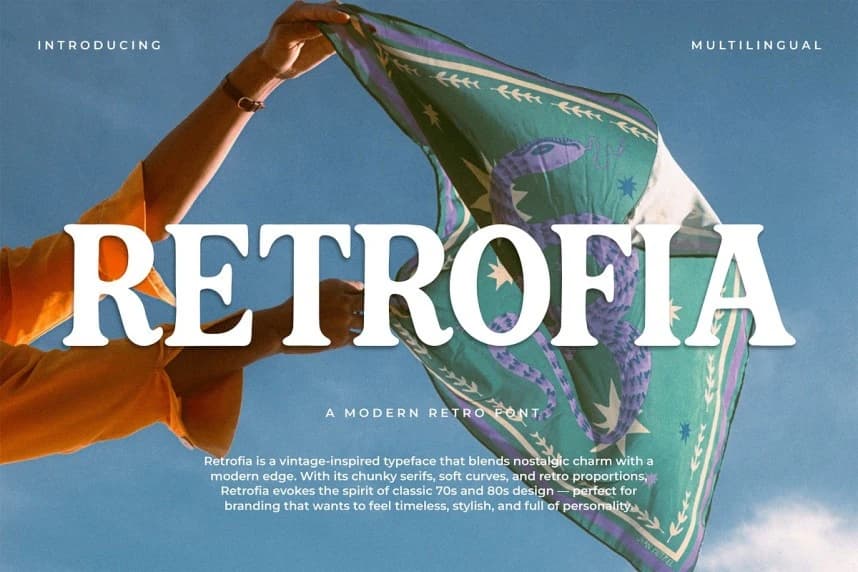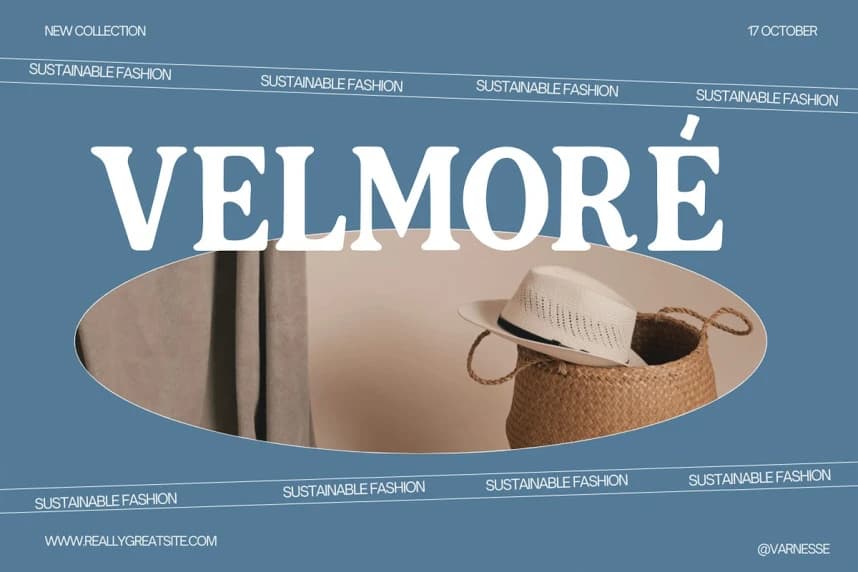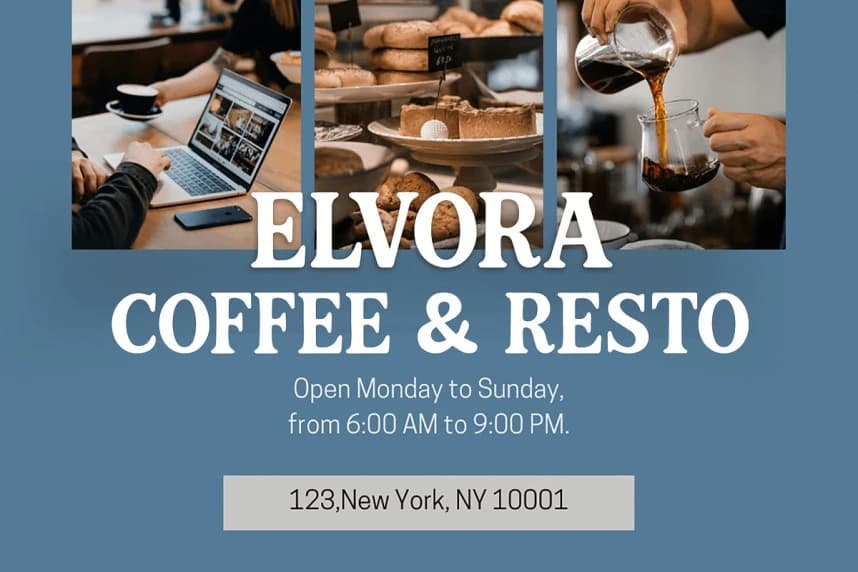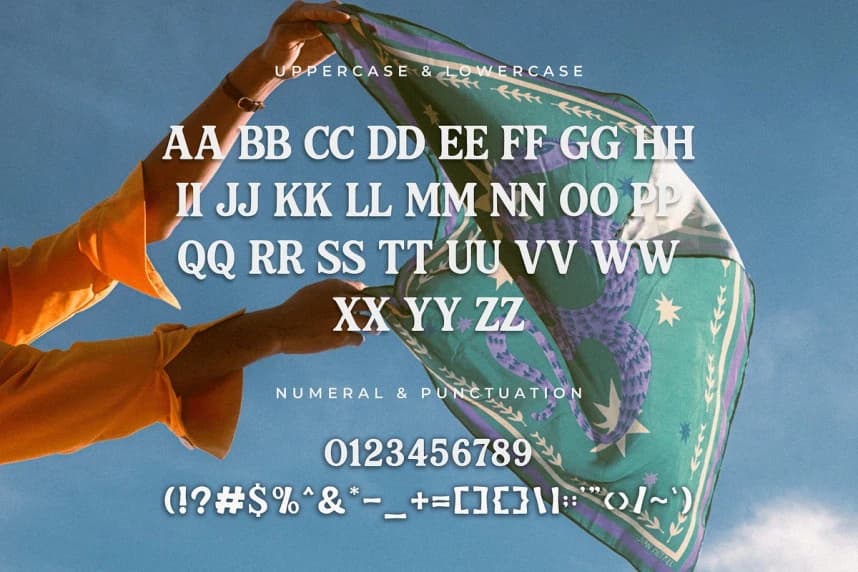
Retrofia Font
Retrofia Font, temiz ve güncellenmiş bir görünümle vintage tasarımın canlı özünü harmanlayan modern bir retro yazı tipidir. Geçmişin groovy harf biçimlerinden ilham alan Retrofia, cesur eğrilere ve oyuncu orantılara sahiptir.
Retrofia Font, vintage tasarımın canlı özünü temiz ve güncel bir görünümle birleştiren modern bir retro fontudur. Geçmişin groovy yazı karakterlerinden ilham alan Retrofia, cesur eğriler ve eğlenceli orantılar sunar.